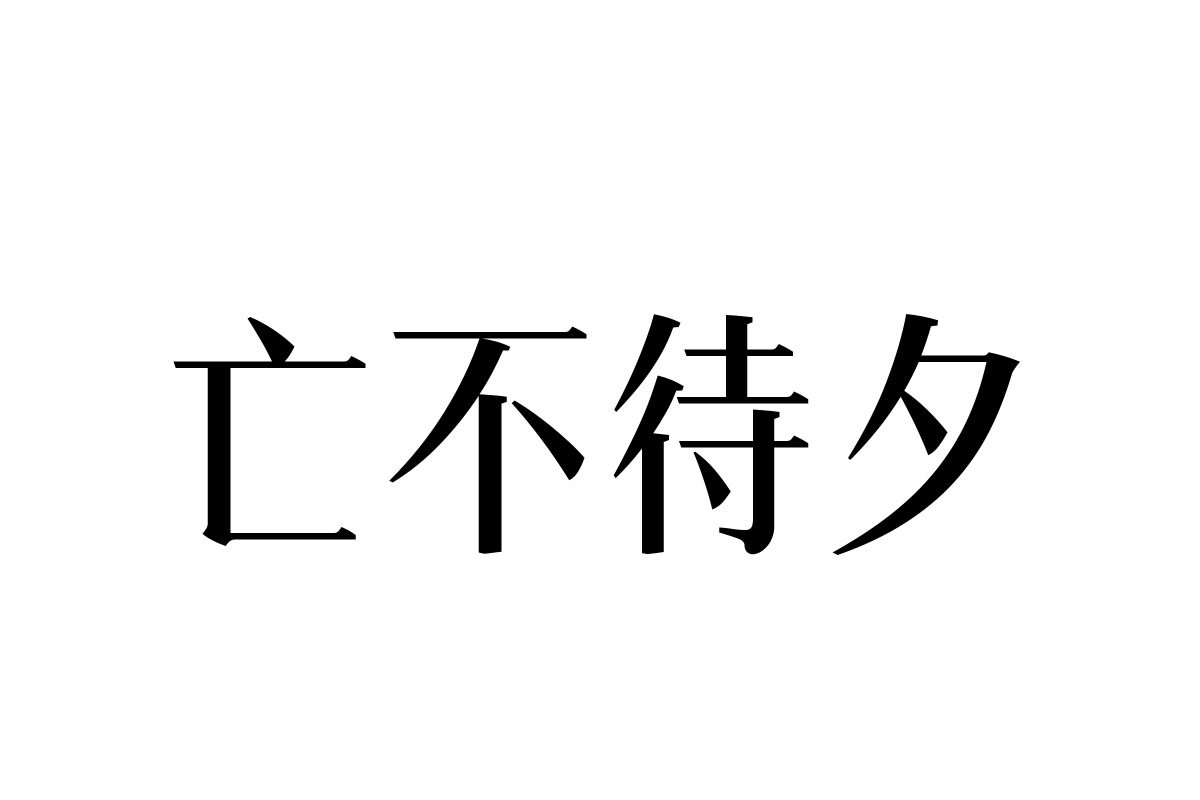
汉仪瑞意宋X_50_Text_W是一款适用于中文排版的字体。它具有优雅的线条,适合用于书籍、杂志、报纸等出版物的文字设计。这款字体的特点是字形简洁大方,笔画流畅,易于阅读。同时,它也能很好地适应各种屏幕显示效果,无论是在电脑屏幕上还是在手机屏幕上都能呈现出良好的视觉效果。总的来说,汉仪瑞意宋X_50_Text_W是一款非常适合中文排版的字体。